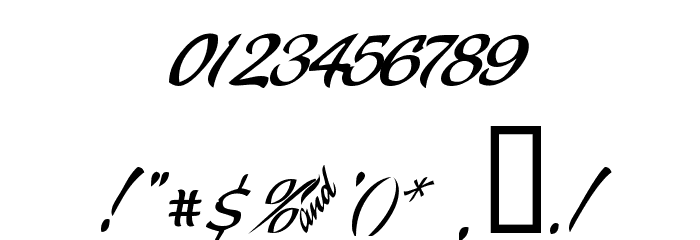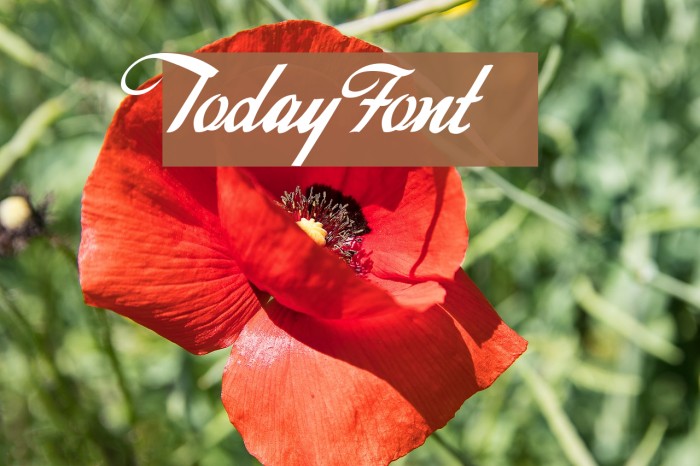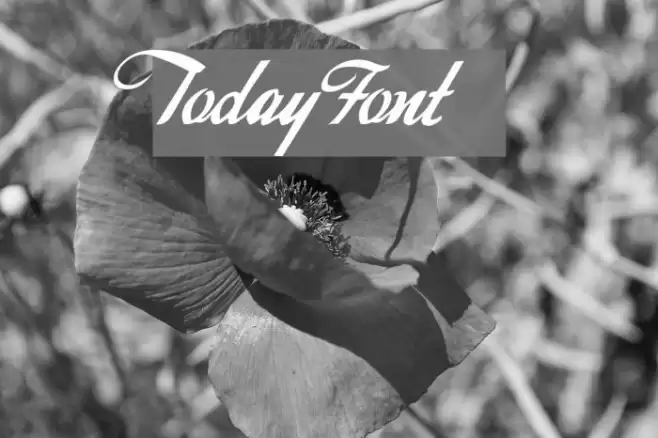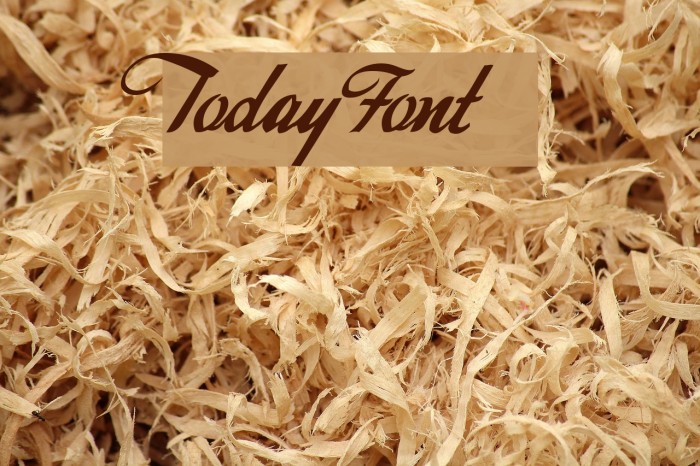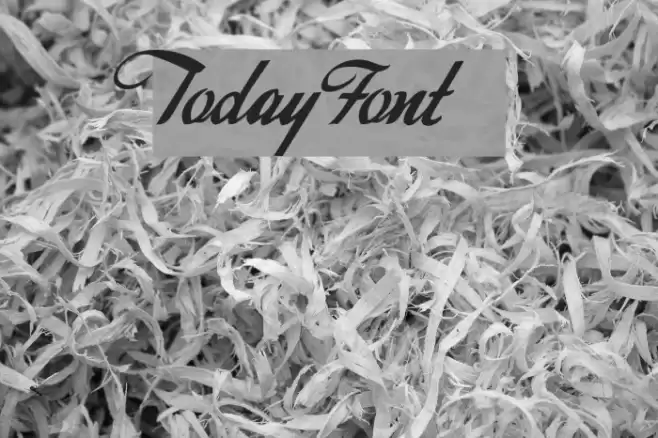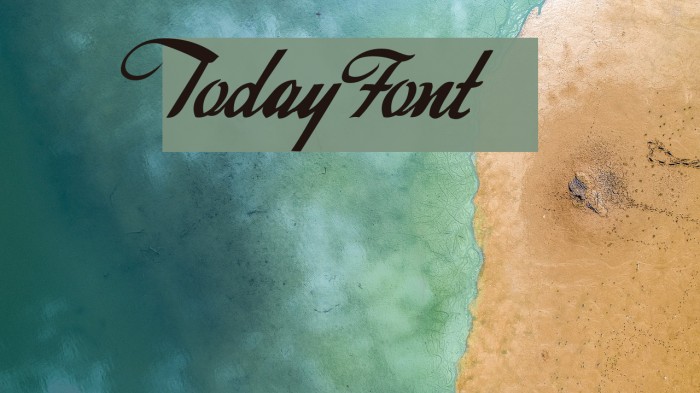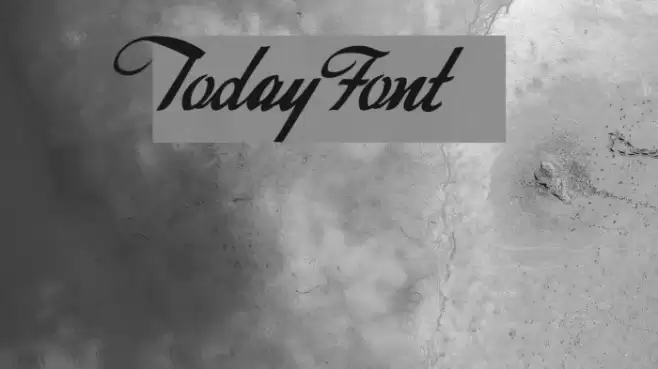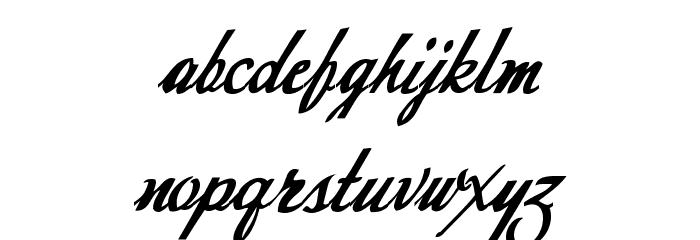
Today Font
| Style général | Classic |
| Cas d'utilisation | Logos, Invitations, Decorative Headlines |
| Projets proposés | Ideal for wedding invitations, elegant branding, luxury product packaging, and decorative headlines. |